Die besten Schriftarten für Ihre WordPress-Vorlage
Veröffentlicht: 2022-10-15Wenn es darum geht, Schrifteigenschaften in einer WordPress-Vorlage zu definieren, gibt es ein paar wichtige Dinge, die Sie berücksichtigen müssen. In erster Linie müssen Sie den allgemeinen Ton und das Gefühl Ihrer Website berücksichtigen. Möchten Sie einen Corporate-Look oder eine entspanntere Atmosphäre? Auf diese Weise können Sie feststellen, welche Schrifteigenschaften für Ihre Anforderungen am besten geeignet sind. Sobald Sie eine allgemeine Vorstellung davon haben, welchen Ton Sie setzen möchten, können Sie damit beginnen, Ihre Schriftartenauswahl einzugrenzen. Wenn Sie nach einem traditionelleren Gefühl suchen, möchten Sie vielleicht bei Serifenschriften bleiben. Diese Schriftarten haben kleine Verzierungen an den Enden ihrer Striche, die ihnen ein klassisches Aussehen verleihen. Wenn Sie einen moderneren Look wünschen, sind serifenlose Schriftarten eine großartige Option. Diese Schriftarten sind sauber und einfach und eignen sich sowohl für große als auch für kleine Textmengen. Wenn Sie endlich ein paar Schriftarten gefunden haben, die Ihnen gefallen, ist es an der Zeit, sie auszuprobieren. Der beste Weg, dies zu tun, besteht darin, einen Testbeitrag auf Ihrer WordPress-Site zu erstellen und zu sehen, wie die Schriftarten in Aktion aussehen. Achten Sie darauf, wie einfach sie zu lesen sind und ob sie zum Gesamtton Ihrer Website passen oder nicht. Mit ein wenig Versuch und Irrtum sollten Sie in der Lage sein, die perfekte Schriftart für Ihre WordPress-Vorlage zu finden.
Wie passe ich die Schriftart in WordPress an?
Die Wahl der Typografie für Ihre Website ist ein wesentlicher Bestandteil des Webdesigns und Brandings. Es ist wichtig, sich daran zu erinnern, dass Schriftarten, wie Farben, Bilder und andere Elemente, eine wichtige Rolle dabei spielen, wie Ihre Besucher Ihre Website sehen. Dies ist eines der Dinge, die Sie mit WordPress für Sie anpassen können. In unserem Kurs lernen Sie alles, was Sie über die Arbeit mit Schriften für WordPress wissen müssen. Ihre Leser werden direkt von den Schriftarten auf Ihrer Website beeinflusst. Wenn Sie möchten, dass Ihr WordPress-Theme eine benutzerdefinierte Schriftart hat, können Sie diese hier finden. Eine der bekanntesten sind die Schriftarten von Google, die fast 1.000 verschiedene Stile bieten.
Wie definieren Sie den Schriftstil des Textes?
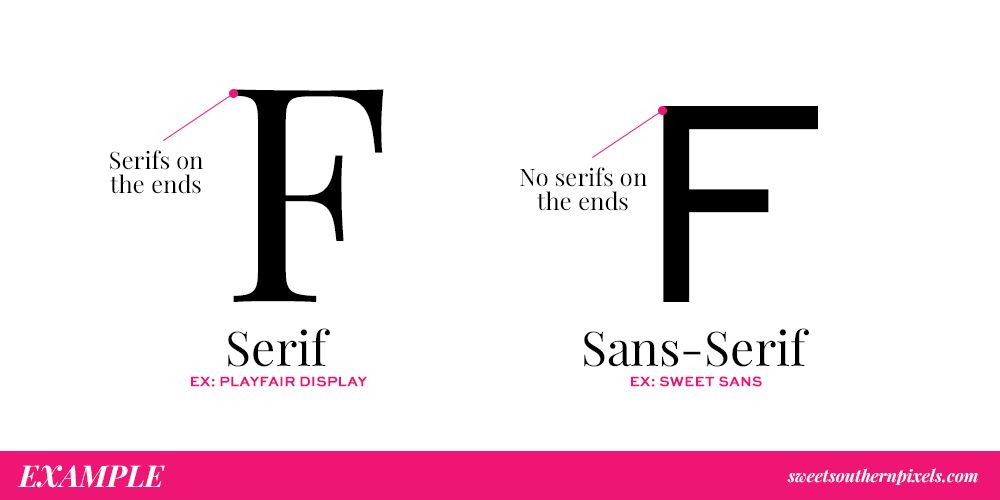
Der Schriftstil des Textes kann als Schreibweise des Textes definiert werden. Dazu können die Schriftart, die Größe der Buchstaben, der Abstand zwischen den Buchstaben und die Farbe des Textes gehören. Der Schriftstil kann auch verwendet werden, um dem Text ein bestimmtes Aussehen oder Gefühl zu verleihen, z. B. um ihn formeller oder lässiger erscheinen zu lassen.
Arten von Schriftarten werden häufig durch ihre Formen, Größen und Stile bestimmt. Die überwiegende Mehrheit der Schriftarten wird nach ihren Kategorien klassifiziert. Die heute am häufigsten verwendeten Schriftarten sind serifenlose, kursive und formelle Schrift. Viele Menschen verwenden immer noch Übergangsschriften mit Serifen, wie z. B. die Baskerville-Schrift. Ein Slab-Serif-Schild wird normalerweise für Geschäfts- oder Filmplakate verwendet. Courier, Rockwell und Clarendon sind einige der beliebtesten modernen Slab-Serif-Schriftarten. Mit Ausnahme einiger geringfügiger Abweichungen ähneln einige humanistische Schriftarten in gewisser Weise einer kursiven Handschrift und verleihen den Schriftarten ein unverwechselbares Aussehen.
Die Buchstaben einer formellen Schreibschrift scheinen von Hand geschrieben zu sein, als ob sie aus der Perspektive eines Kalligraphen geschrieben wären. Während einige dekorative Schriftarten bestimmte Buchstaben extrem stark akzentuieren, wirken andere eher gedämpft auf die natürliche Art und Weise, in der kursive Handschrift geschrieben wird. In Präsentationen oder Korrespondenz, die eine geschäftliche Präsentation erfordern, wird normalerweise eine moderne Serifen- oder Sans-Serif-Schriftart bevorzugt. Courier New, Times New Roman, Helvetica, Calibri und Arial sind die Schriftarten, die die meisten Menschen in ihrer täglichen Kommunikation verwenden.
Das Ende eines Serifenbuchstabens wie Times New Roman wird durch dekorative Schnörkel gekennzeichnet. Der Begriff „Serifensand“ bezieht sich auf Designs, denen diese dekorativen Schnörkel fehlen und die weniger formell erscheinen. Formale Schreibschriften wie die Garamond sind häufig eleganter und können für formelles oder akademisches Schreiben verwendet werden. Beim Erstellen von Inhalten können Sie eine Vielzahl von Schriftarten verwenden, um ein ansprechenderes Erscheinungsbild zu erzielen. Eine formalere oder kunstvollere Schriftart kann sich gut für das hochwertige Erscheinungsbild eines Inhalts eignen. Darüber hinaus kann die Verwendung einer Schriftart, die auf einem kleinen Bildschirm gut lesbar ist, dazu beitragen, die Chancen zu erhöhen, dass Menschen den Inhalt entdecken. Es gibt eine Vielzahl von Schriftarten, die für verschiedene Arten von Inhalten geeignet sind. Ganz gleich, ob Sie ein detaillierteres Erscheinungsbild erstellen oder die Zugänglichkeit Ihrer Inhalte verbessern möchten, die Verwendung der richtigen Schriftart kann einen großen Unterschied machen.
Wie ändere ich die Schriftart in WordPress 2022?
Das Plug-in enthält Schriftdateien in Appearance, auf die über das Menü des Plug-ins zugegriffen werden kann. Sie können die Typografie Ihres WordPress-Dashboards ändern, indem Sie auf die Registerkarte „Typografie“ klicken. Auf dem folgenden Bildschirm sehen Sie ein Menü mit der Bezeichnung „Standardtypografie“. Es ist jetzt einfach, es auszuwählen, indem Sie darauf klicken. Ihre Website verfügt nun über Schriftartoptionen für alle Elemente.
Wenn Ihre Website den gleichen Schriftstil, die gleiche Schriftgröße und die gleiche Schriftfarbe hat, wirkt sie langweilig und unprofessionell. WordPress ist ein fantastisches Tool zum Ändern Ihrer Schriftart. Sie können eine Seite/einen Beitrag auffälliger gestalten, indem Sie für jede Überschrift eine andere Schriftgröße verwenden. Ein weiterer Vorteil der Verwendung verschiedener Schriftstile und -farben besteht darin, dass Ihre Website optisch ansprechender wird. Der Zakra Theme Customizer bietet zwei Typografieoptionen. In H1 gibt es eine Basisüberschrift, während es in H6 eine Basisüberschrift gibt. Sie können die Typografie der Fußzeile, Kopfzeile, Seitenleiste und des Beitrags/der Seite selbst ändern.
Sie können die Schriftart des Dropdown-Menüs ändern, indem Sie die Option Primäres Menü: Dropdown-Element auswählen. Navigieren Sie vom WordPress-Dashboard zu den Seiten. Nachdem Sie Bearbeiten ausgewählt haben, können Sie die Schriftart der Seite ändern, die Sie bearbeiten möchten. Bitte scrollen Sie erneut nach unten, um die Typografie des Titels des Blog- oder Archivbeitrags zu ändern. Es ist auch möglich, die Schriftgrößen für Klein, Normal, Mittel, Groß und Riesig zu ändern. Auf Ihr WordPress-Dashboard können Sie zugreifen, indem Sie auf Seiten klicken. Sie können einen Textabschnitt bearbeiten, indem Sie ihn auswählen und auf Bearbeiten klicken. Sie können auch die Ausrichtung, Dicke und den Typ von Absätzen in Überschriften (h1-h6) ändern. Sie müssen dann auf die Schaltfläche Aktualisieren oder Veröffentlichen klicken, was Sie tun können, nachdem alle Änderungen vorgenommen wurden.
So ändern Sie die Schriftart in Ihrem WordPress-Adminbereich
Um die Schriftart Ihres WordPress-Adminbereichs zu ändern, gehen Sie zum Admin-Dashboard und wählen Sie Einstellungen. Die Option Admin-Schriftart wird angezeigt und Sie können die Schriftart auswählen, die Ihren Anforderungen am besten entspricht.
Liste der WordPress-Schriftarten
Es gibt ein paar großartige Orte, um eine Liste mit WordPress-Schriftarten zu finden. Einer ist durch WordPress selbst. Gehen Sie in Ihrem WordPress-Dashboard zur Seite Aussehen > Schriftarten . Hier sehen Sie eine Liste aller Schriftarten, die Ihnen zur Verfügung stehen. Ein weiterer großartiger Ort, um eine Liste mit WordPress-Schriftarten zu finden, ist Google Fonts.
WordPress-Schriftarten können verwendet werden, um Nachrichten auf verschiedene Weise zu senden, einschließlich der Freude an den Augen des Benutzers. Wenn Schriften auf die gleiche Weise reagieren wie eine Farbe oder ein Bild, erzeugen sie Emotionen. In diesem Artikel werden wir uns ansehen, wie wichtig Schriftarten in WordPress sind, sowie eine Liste von zwölf Schriftarten, die die meisten Menschen nützlich finden werden. Sans-Serif, eine Serifenschrift, ist eine beliebte Schriftart. Sie werden daran interessiert sein, wenn Sie Droid gut kennen und es schon einmal benutzt haben. Droid ist von Droid abgeleitet. Wenn Sie es also kennen und schon einmal benutzt haben, ist dies das richtige Telefon für Sie. Es ist eine Schrift von Natanael Gama, die zur lateinischen Familie gehört und als Erweiterung von Exo eingeführt wurde.
Zusätzlich zu Websites, mobilen Schnittstellen und Druckmaterialien kann Open Sans verwendet werden, um mobile Apps zu erstellen. Playfair Display, BenchNine, Slabo, Oswald und Lato gehören zu den besten WordPress-Schriftarten für Vintage-inspirierte Blogs. Claus S*rensen hat Playfair Display 2013 als Soloprojekt ins Leben gerufen und ist seitdem ein beliebtes Produkt geblieben. Der volkstümliche Holzschnitttyp wird von BenchNine kopiert, der von Tintenblutungen inspiriert ist. Lora, eine ausgewogene Serifenschrift, wurde von der Rundung der Kalligrafie inspiriert. Source Sans Pro von Adobe wurde entwickelt, um die Anforderungen einer Vielzahl von Benutzertypen zu erfüllen. Monserrat hat eine globale Reichweite und wird von mehr als 5 Milliarden Websites verwendet.
Der beste Weg, Schriftarten zu paaren: 5 Tipps und Tricks, die Ihnen helfen können, sich ein besseres Bild von Ihren bevorzugten Schriftarten zu machen Bei der Gestaltung Ihrer Titel, Inhalte und Menüs sollten Sie ein gewisses ästhetisches Prinzip beachten. Es gibt zwei Möglichkeiten, kontrastreiche Schriftarten zu verwenden: dünn oder fett. Sie müssen darauf achten, dass sich die von Ihnen verwendeten Schriftarten ergänzen. Wenn die Schriftarten Ihrer Website keine gemeinsamen Elemente aufweisen, sieht sie eintönig aus.